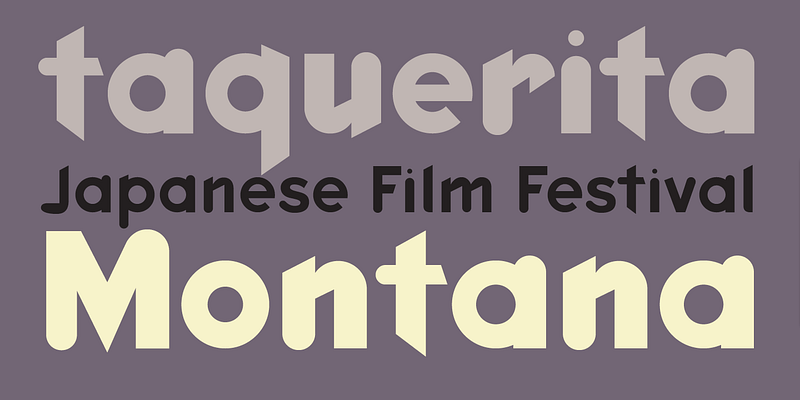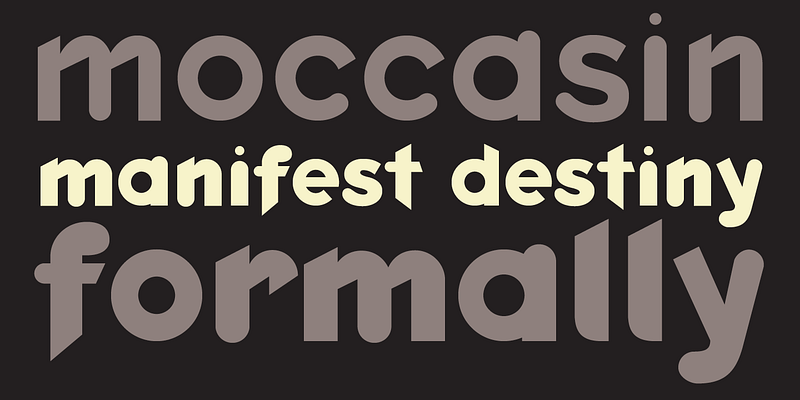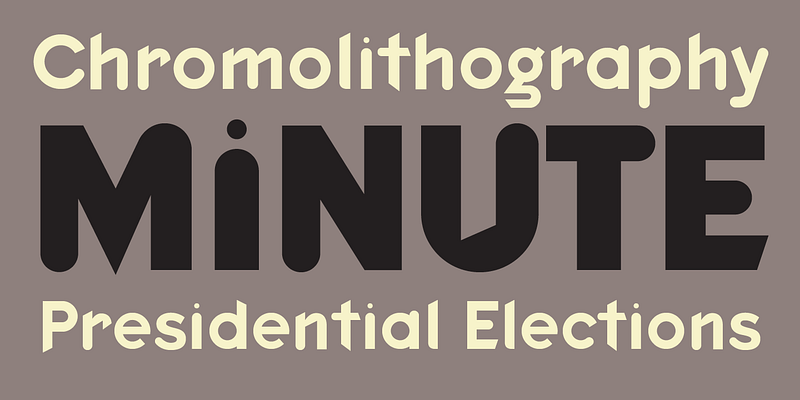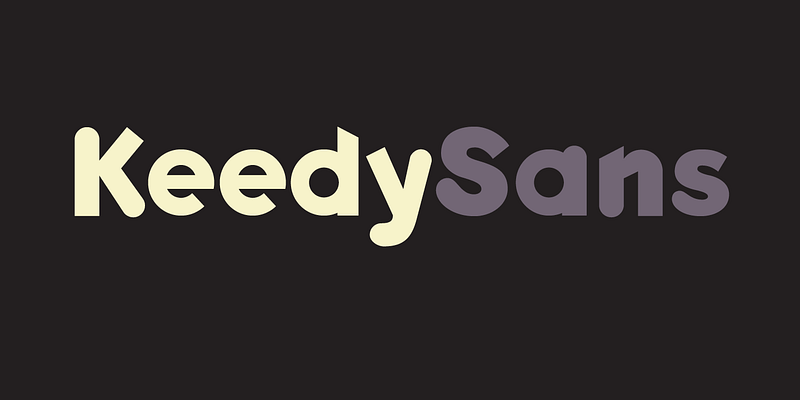
Wie viele Grafikdesigner in den späten 1980er und frühen 1990er Jahren wollte Jeffery Keedy den Computer als Werkzeug nutzen, war aber frustriert über die begrenzte Auswahl an digitalen Schriften. Die daraufhin geschaffene Keedy Sans wurde in Layouts für die Zeitschrift Emigre verwendet und von Designern in aller Welt angenommen.
Keedy Sans hat eine ähnliche Bedeutung wie eine andere wichtige Emigre-Schrift, die Dead History von P. Scott Makela, die ihren experimentellen Charakter mit absichtlich unvollendeten und inkongruenten Buchstabenformen unterstreicht. „Die meisten Schriften sind logisch systematisch aufgebaut; wenn Sie ein paar Buchstaben sehen, können Sie ziemlich genau erraten, wie der Rest der Schrift aussehen wird. Ich wollte eine Schrift, die diesen Erwartungen absichtlich widerspricht“, sagte Keedy.
Im Jahr 2011 war Keedy Sans eine von 23 digitalen Schriften, die in die ständige Architektur- und Designsammlung des Museum of Modern Art in New York aufgenommen wurden.